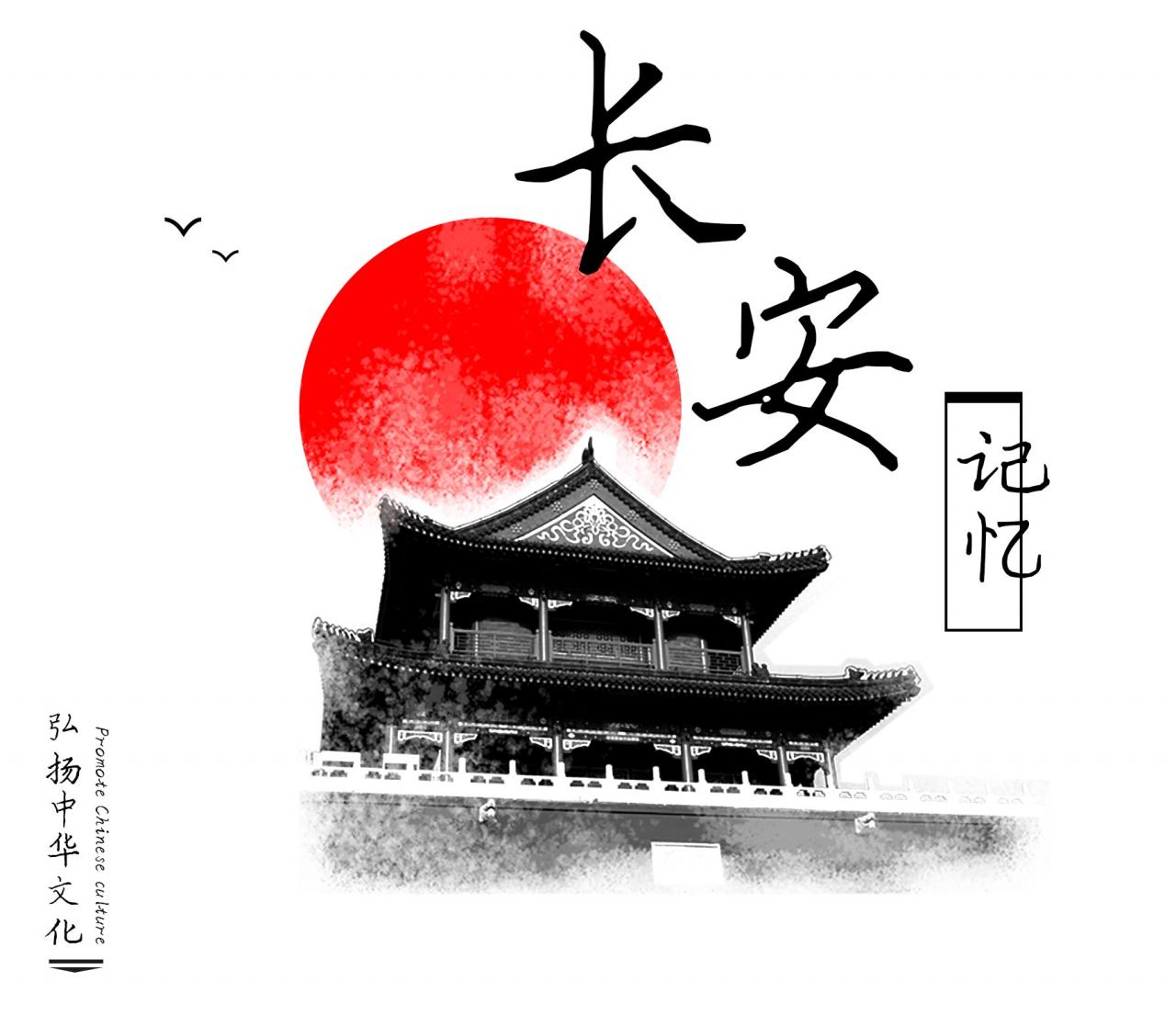
字体名称:三极文明楷书
设计师:吴润
所属分类:常规书写·硬笔
三极文明楷书结构严谨,既有颜体的雄浑,又不失赵体的飘逸。严谨秀气而从容和优雅,让人赏心悦目,百看不厌。可广泛用于书刊、广告、包装、影视以及社交网络个性化用字。
适用媒介:报纸、杂志、书籍、广告、宣传册、包装、影视、屏幕显示、交互设计。